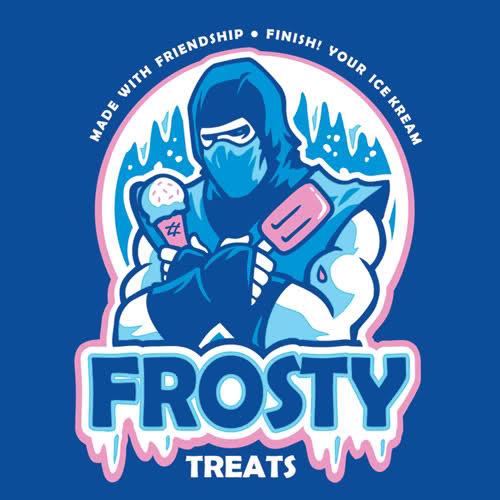
Suche Schrift zum Shirt-Logo!
Und zwar suche ich schon lange eine solche Schrift:
Es geht also in erster Linie um das Kursive S.
Was meinst Du denn mit kursiv? Da kommen gar keine kursiven Buchstaben vor in Deinem Beispiel. Ich vermute mal, Du meinst einfach die spezielle Form des Buchstabens »S«, richtig?